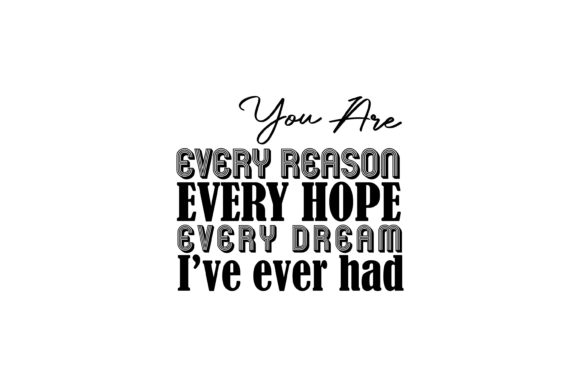
Every Hope-Love Quotes Font
การค้นหาองค์ประกอบการออกแบบที่เหมาะสมอาจเป็นเรื่องท้าทาย แต่ Every Hope-Love Quotes Font นำเสนอคอลเลกชันที่โดดเด่นซึ่งช่วยยกระดับงานของคุณได้ทันที
สร้างขึ้นอย่างแม่นยำ Every Hope-Love Quotes Font ให้เวกเตอร์ที่สะอาด พิมพ์ตัวอักษรที่ราบรื่น และใบอนุญาตเชิงพาณิชย์เพื่อความสบายใจ
ไม่ว่าคุณจะสร้างผลิตภัณฑ์ POD (Print on Demand) คำเชิญงานแต่งงาน หรือกราฟิกโซเชียลมีเดีย Every Hope-Love Quotes Font ก็เหมาะสมอย่างยิ่ง